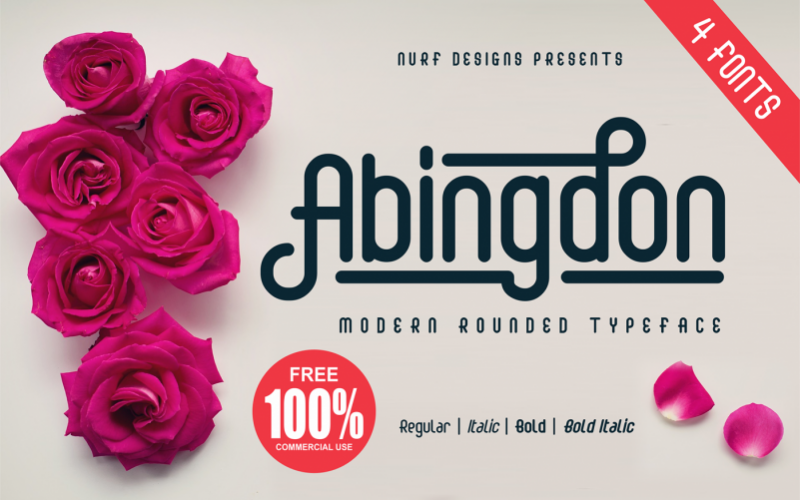
Abingdon Free Font – Download Grátis
A fonte Abingdon Free Font é uma delícia para projetos digitais que buscam alegria de forma moderna e elegante. Feita pelo designer Hamilton, ela traz um toque suave de curvatura às letras, criando um tipo com uma personalidade marcada e versátil. Ideal tanto para apresentações como para elementos gráficos em geral, essa fonte está perfeita para destacar títulos, frases-chave ou até mesmo assinaturas e marcas. Não existe a necessidade de qualquer programa adicional para usar Abingdon Free Font – basta instalá-la e começar a explorar seus potenciais. Suavizar seu design com apenas um clique é tão fácil quanto instalar uma nova fonte no seu computador. Esta font é perfeita tanto para logos, convites, rótulos, cabeçalhos ou até mesmo postais de aniversário. Abingdon Free Font é a escolha certa se você está à procura de um tipo que vai dar ao seu projeto o toque final necessário.